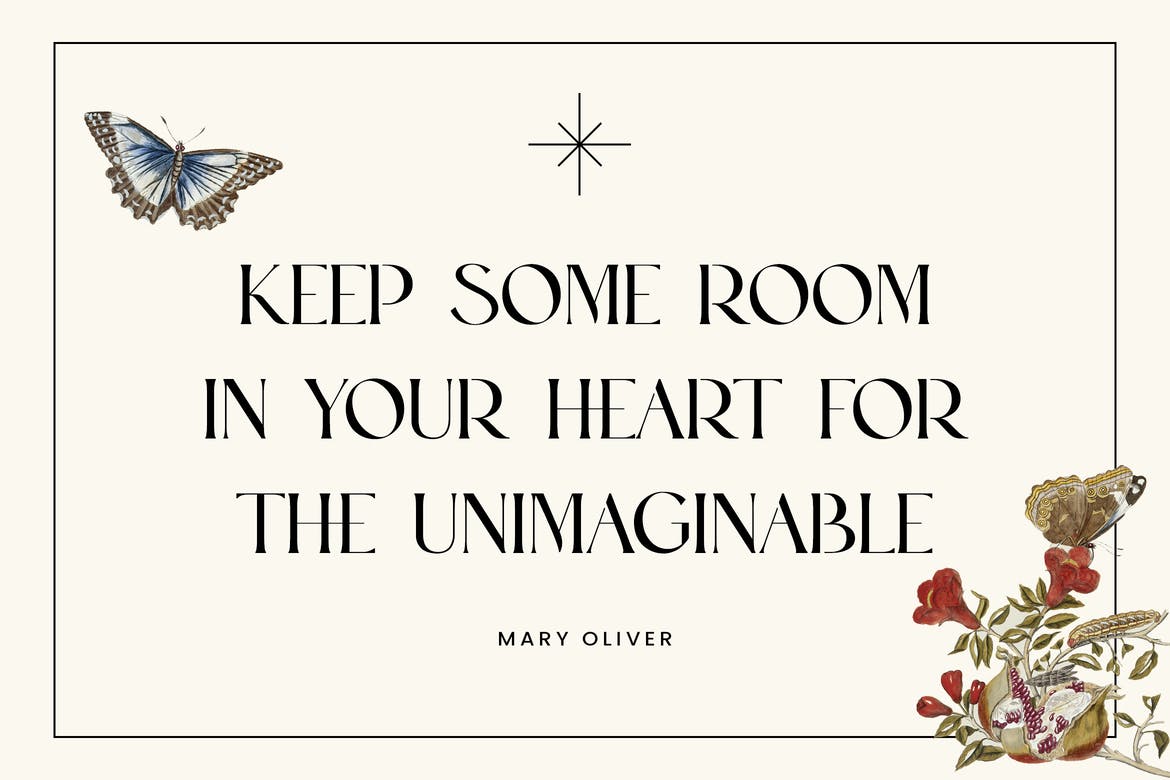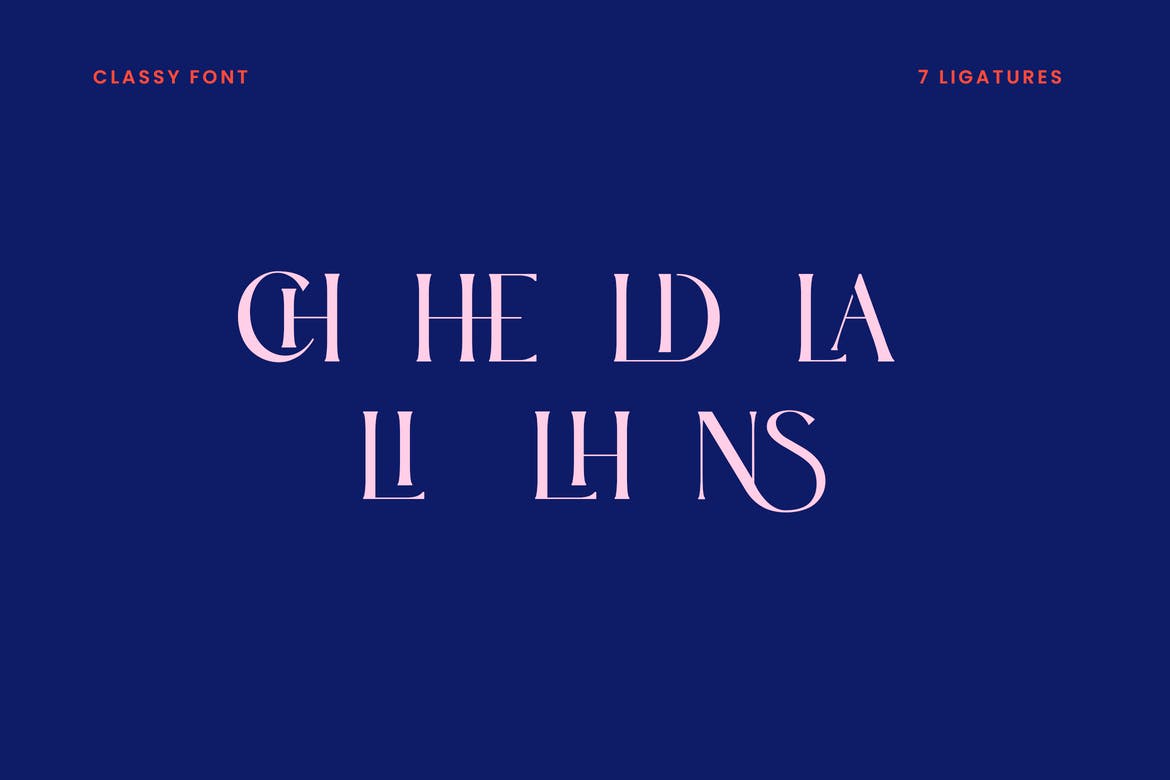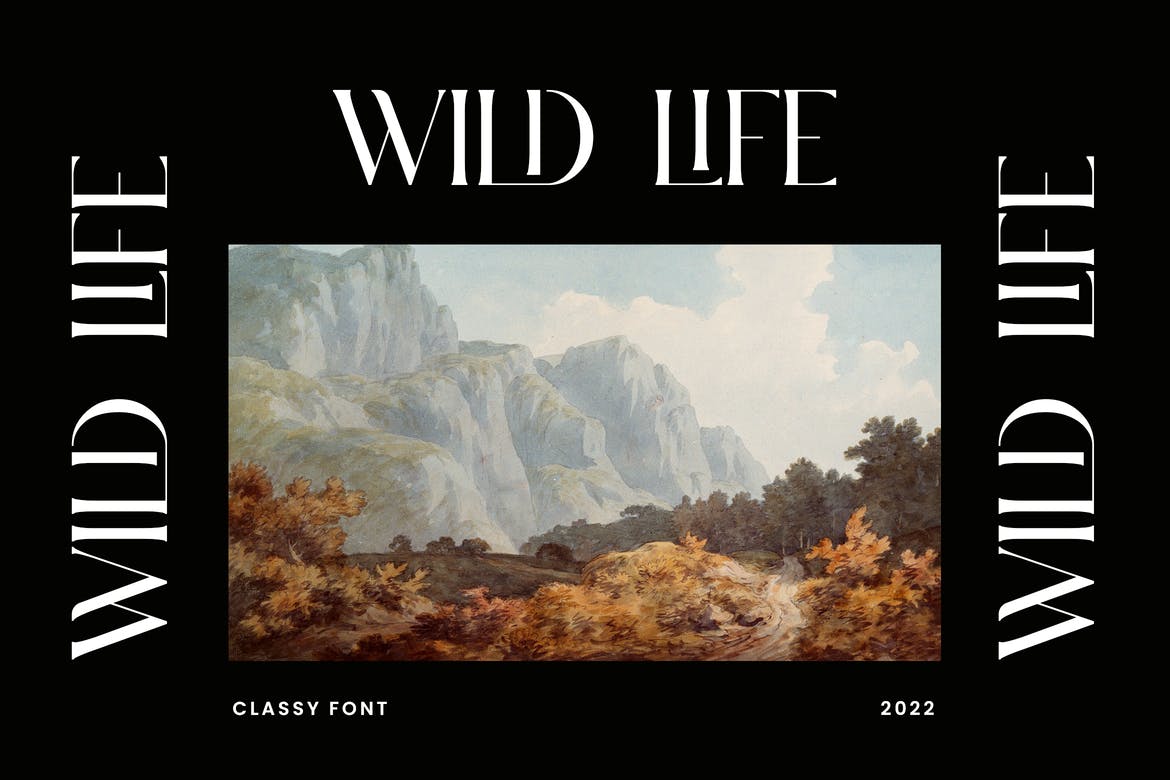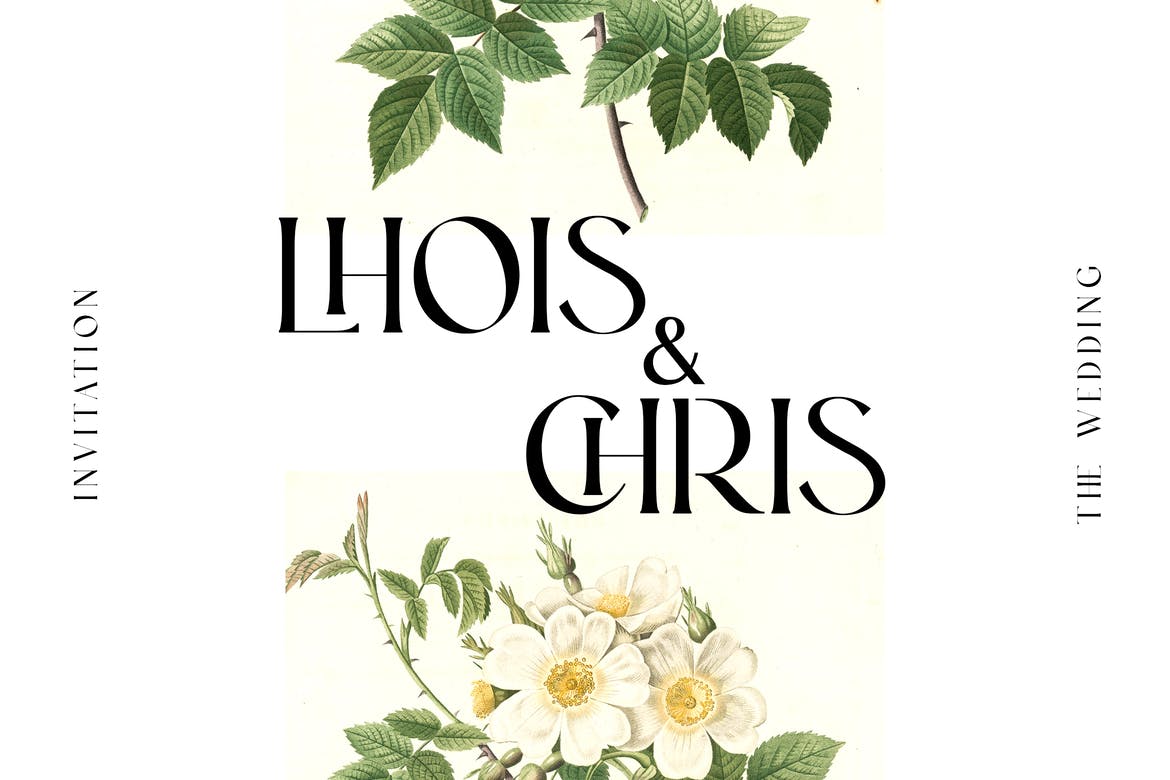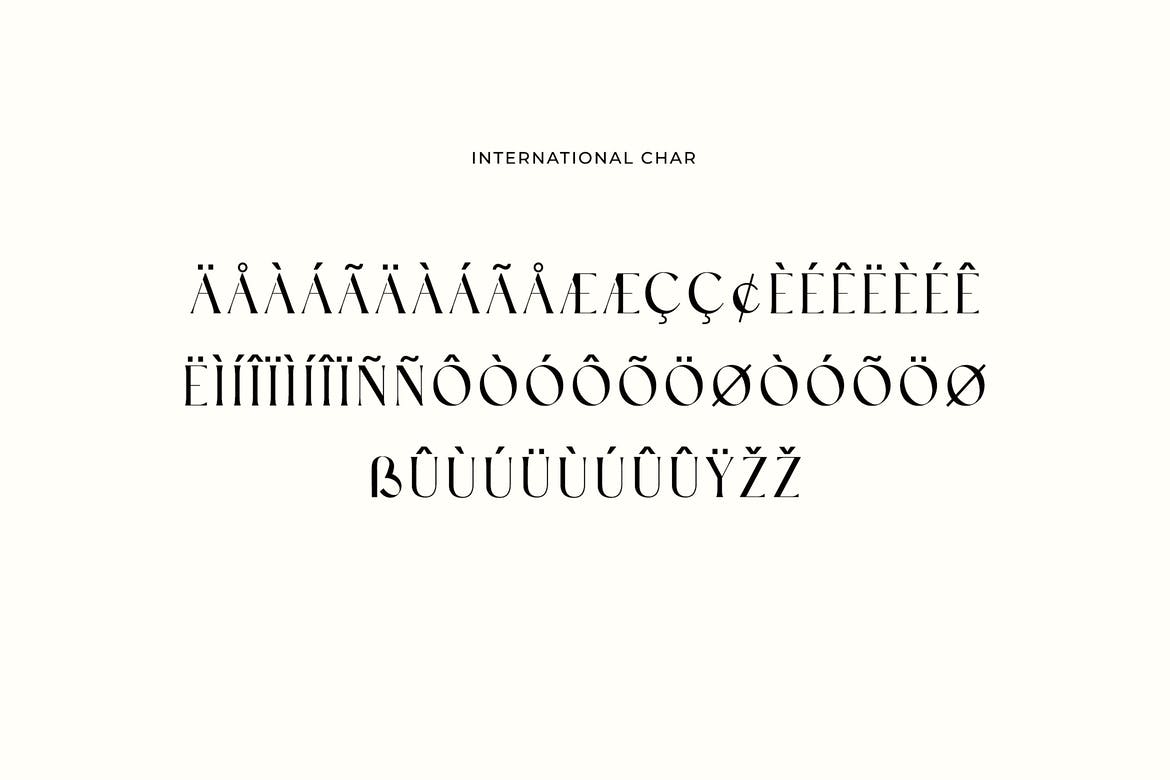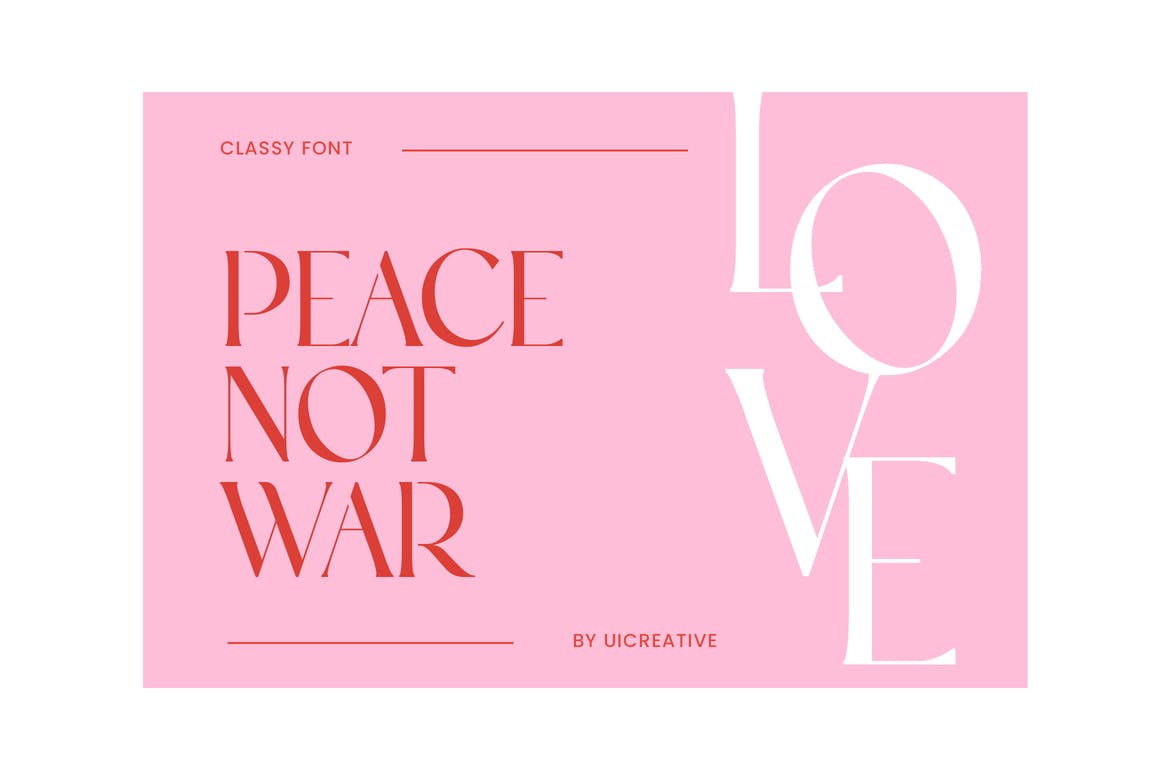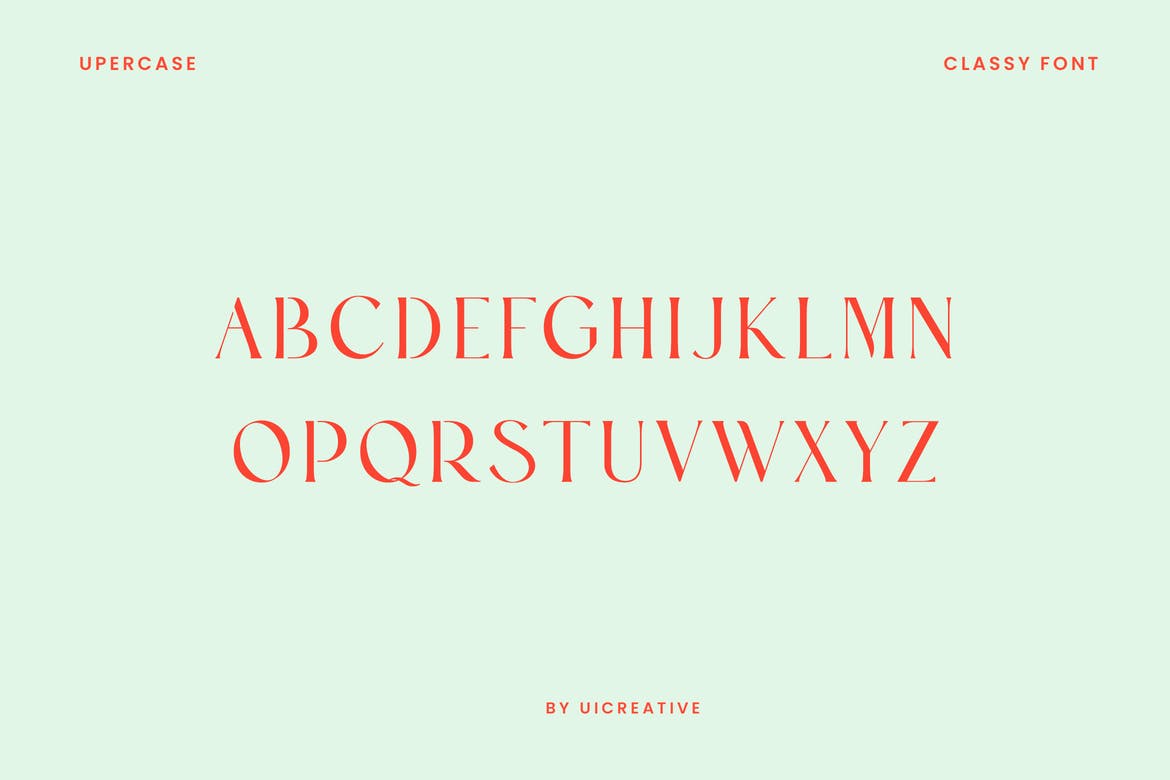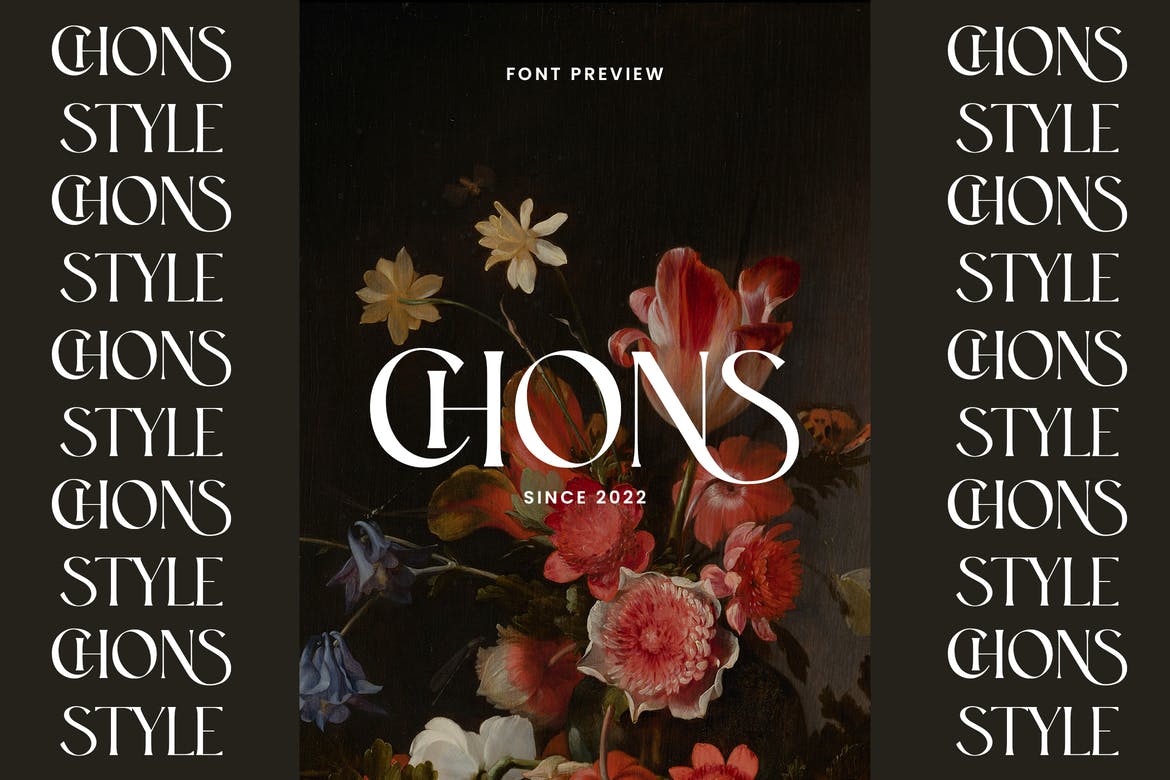
دانلود فونت لوکس و شیک Bohemian Stylish
Bohemian Stylish Luxury Serif Font
فونت Bohemian Stylish یک انتخاب ایده‌آل برای طراحی‌های مدرن و شیک است.
معرفی محصول جدید ما: فونت لوکس و شیک Bohemian Stylish. این فونت Serif مدرن، احساسی زیبا، کلاسیک، و شیک را به همراه دارد. این فونت به‌طور کامل برای انواع پروژه‌ها مناسب است، مانند امضا، لوازم‌التحریر، لوگو، طراحی عروسی، نقل‌قول‌های تایپوگرافی، جلد مجله یا کتاب، سرصفحه وب‌سایت، لباس، برندینگ، طراحی بسته‌بندی و بیشتر. همچنین، برندینگ یا طراحی ویرایشی مرتبط با مد، هر دو ویژگی‌های مردانه و زنانه را به نمایش می‌گذارد.